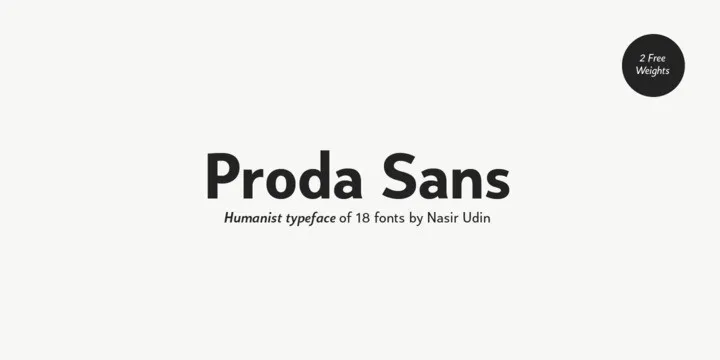
A Proda Sans Serif Font é uma tipografia moderna, simples e legível que se adapta perfeitamente para diversos usos visuais. Seu design minimalista foi criado por Nasir Udin na plataforma de propostas 99designs. Perfeita para a identidade visual dos produtos Minight ou qualquer outro projeto digital, como redes sociais, roupas texturizadas e até mesmo embalagens de livros. Inspirada nos modelos de tipo humanistas do início da década de 1950, a Proda foi projetada com uma aparência geométrica para manter sua legibilidade, apesar das diferenças nas linhas mais leves que proporcionam um contraste visual distintivo. Com seu tamanho x-height médio, essa tipografia adquire um ar encorpado e delicado, mantendo o foco em seu conteúdo principal. É uma opção ideal para quem busca um equilíbrio entre simplicidade e eficácia na legibilidade, criando ambientes visuais agradáveis que destacam sua mensagem ou design.